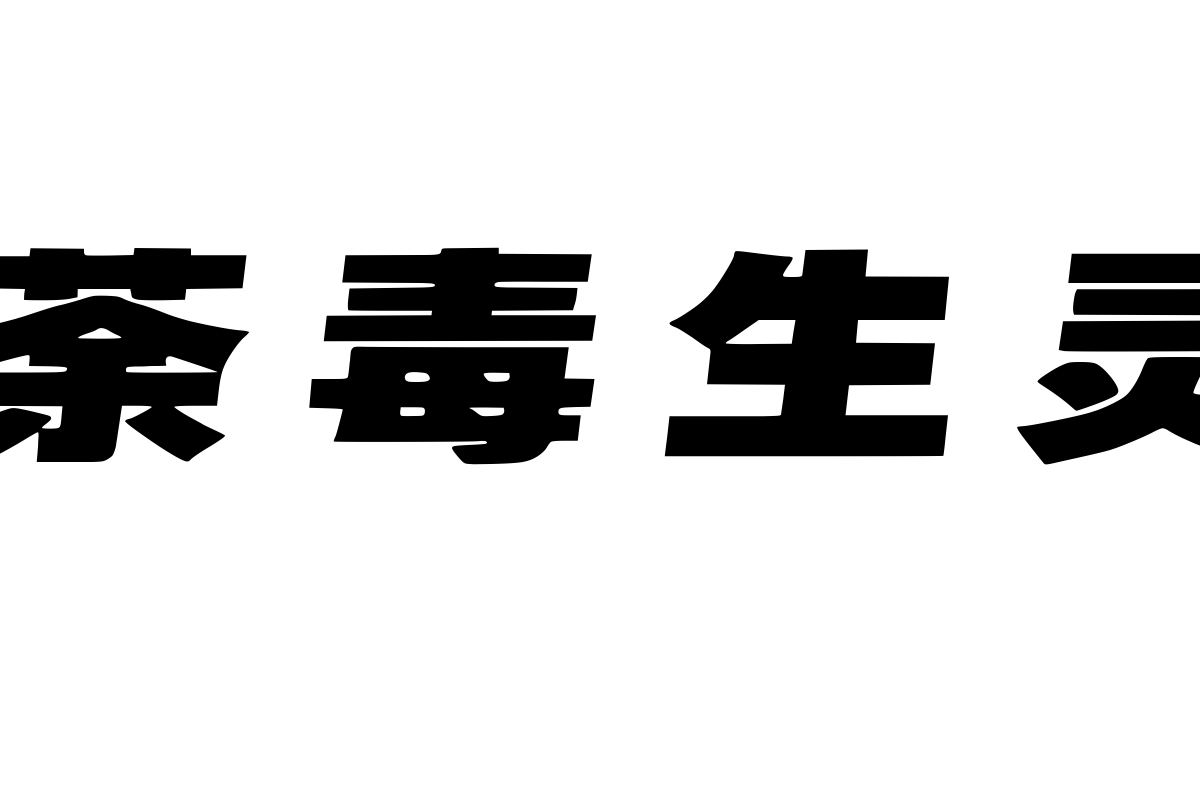
汉呈王天喜格局体是一款具有独特风格的中文字体,它结合了传统书法的韵味与现代设计的审美,为设计师和艺术家提供了丰富的创作灵感。这款字体的特点如下:
1. 字形结构:汉呈王天喜格局体采用独特的字形结构,使得每个字都呈现出独特的美感。这种结构使得字体既有古典的韵味,又不失现代感。
2. 笔画流畅:汉呈王天喜格局体的笔画线条流畅自然,没有过多的装饰性元素,使得字体显得简洁而有力。这种流畅的笔画线条使得字体在视觉上更加和谐,易于阅读。
3. 风格独特:汉呈王天喜格局体将传统书法的元素融入现代设计中,使得字体既有古典的韵味,又不失现代感。这种独特的风格使得字体在众多字体中脱颖而出,具有较高的辨识度。
4. 适用范围广:汉呈王天喜格局体适用于各种设计场景,包括海报、广告、网页设计、书籍排版等。它的通用性和灵活性使得设计师能够根据不同的需求选择合适的字体进行应用。
总之,汉呈王天喜格局体是一款具有独特风格和广泛应用前景的中文字体。它融合了传统书法的韵味与现代设计的审美,为设计师和艺术家提供了丰富的创作灵感。无论是用于商业还是艺术设计,汉呈王天喜格局体都能展现出其独特的魅力。